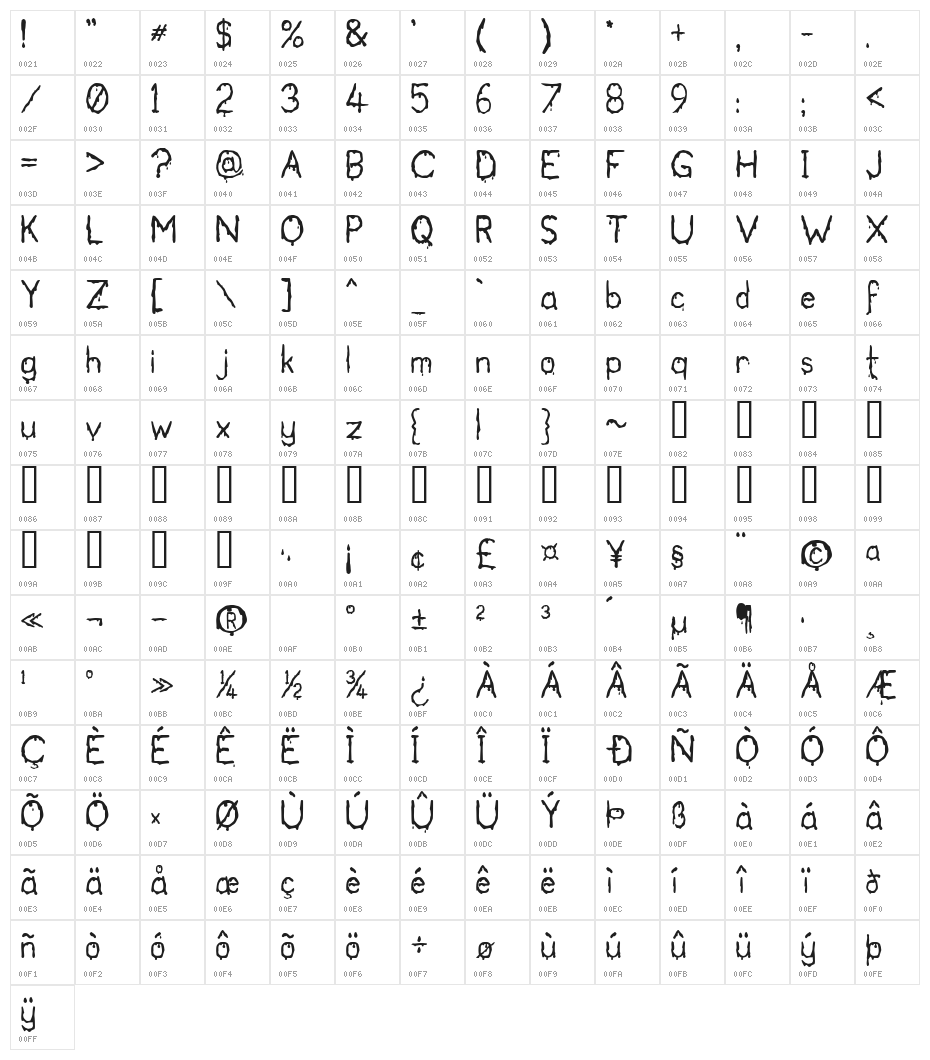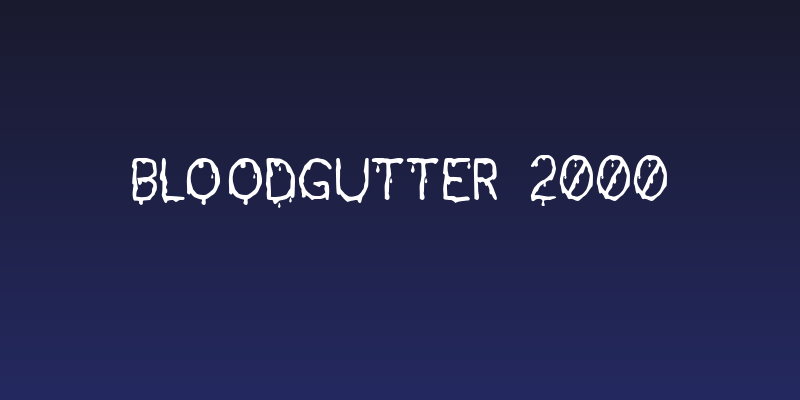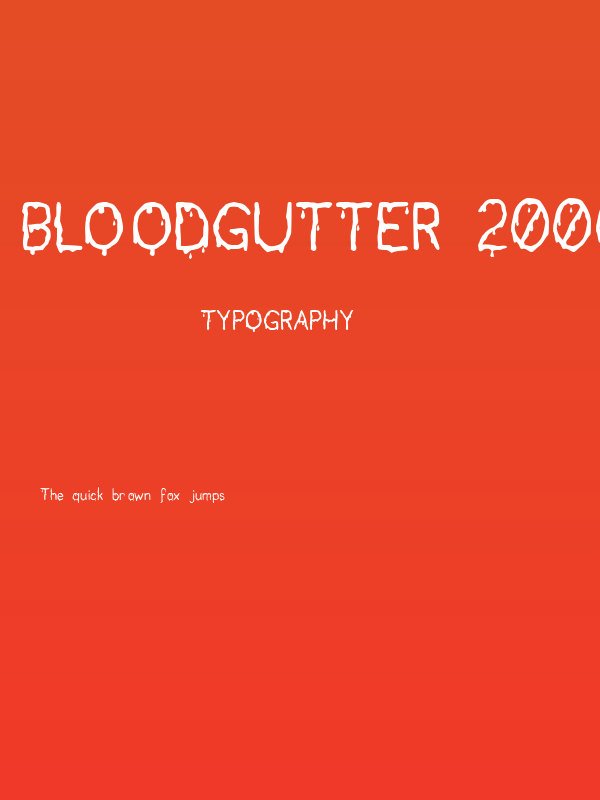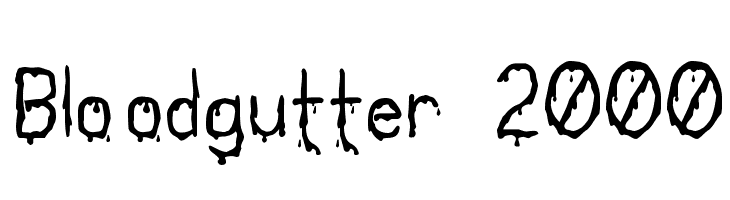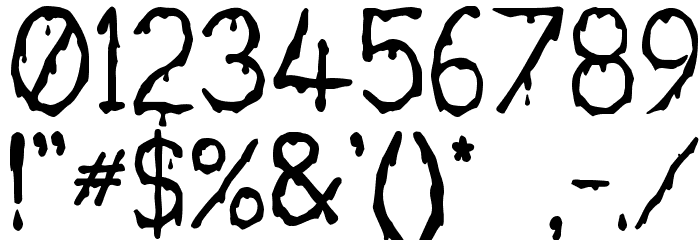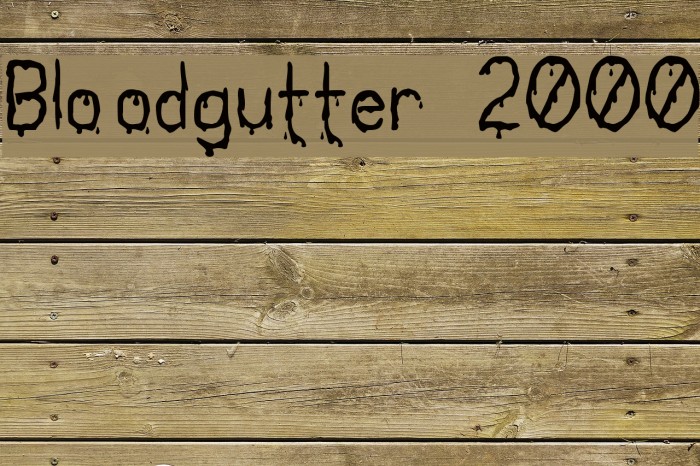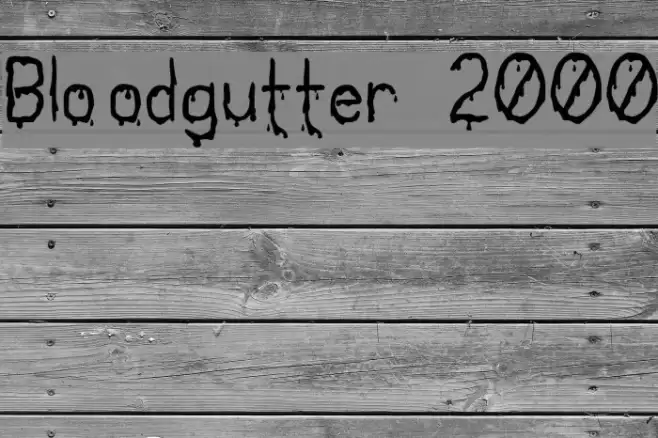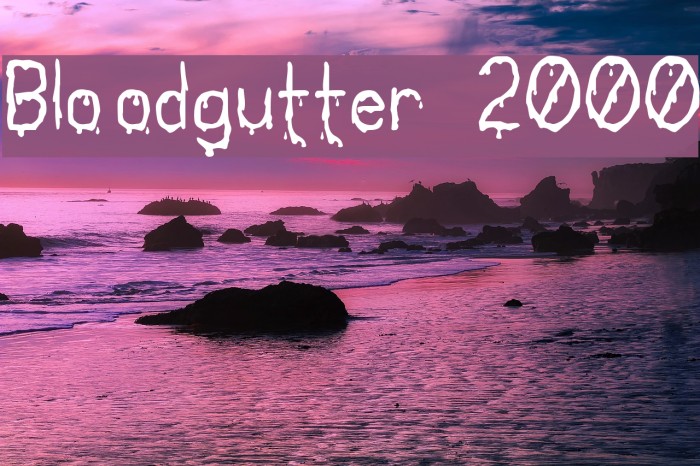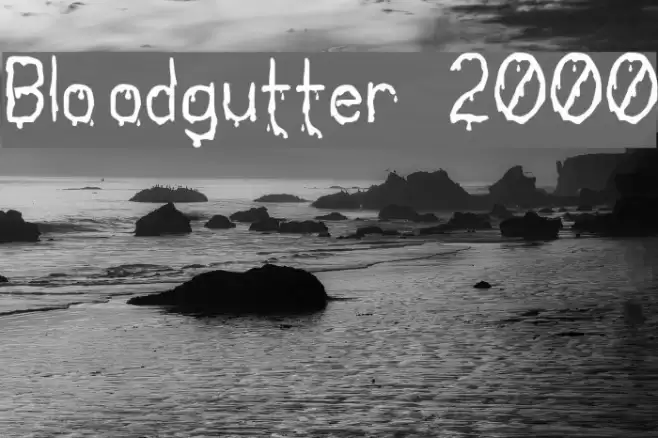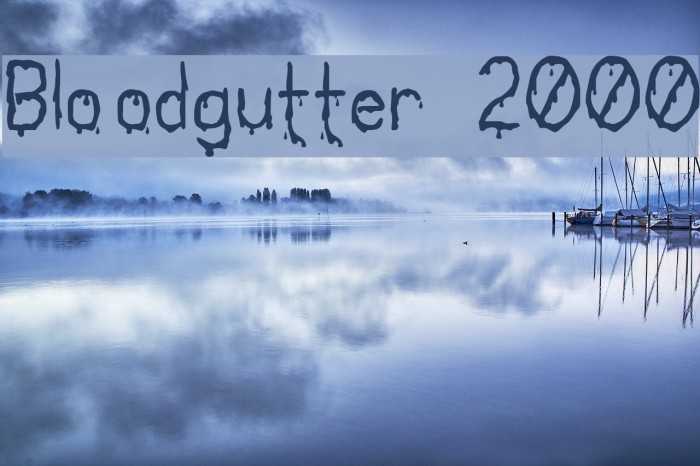
Bloodgutter 2000 Font
| Vorgeschlagene Projekte | Ideal for Halloween posters, horror movie titles, spooky event invitations, and themed merchandise. |